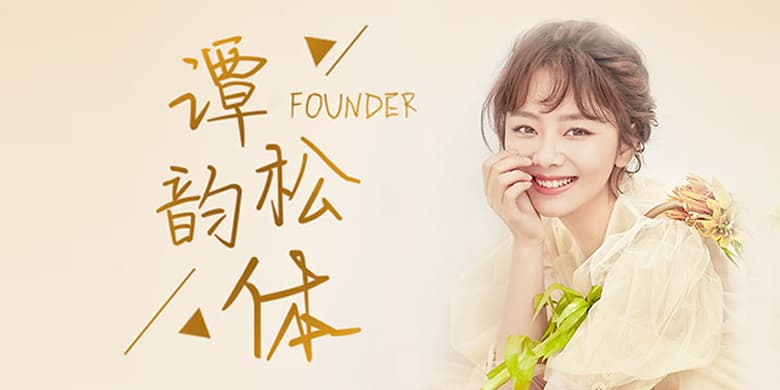
品牌:方正手迹设计师:谭松韵发行时间:2020字库编码:大陆简体(GB2312-80)分类:常规书写·硬笔字体属性:精品字
方正手迹-谭松韵体,由中国内地影视女演员谭松韵创作。该字字形多变,且轻盈飘逸、内紧外松、别具一格,笔画线条简洁明快、恣意洒脱,恰如女孩子古灵精怪、单纯率直的特点。适用于现代诗歌、短文的排版以及文化、商业类品牌的广告语设计。